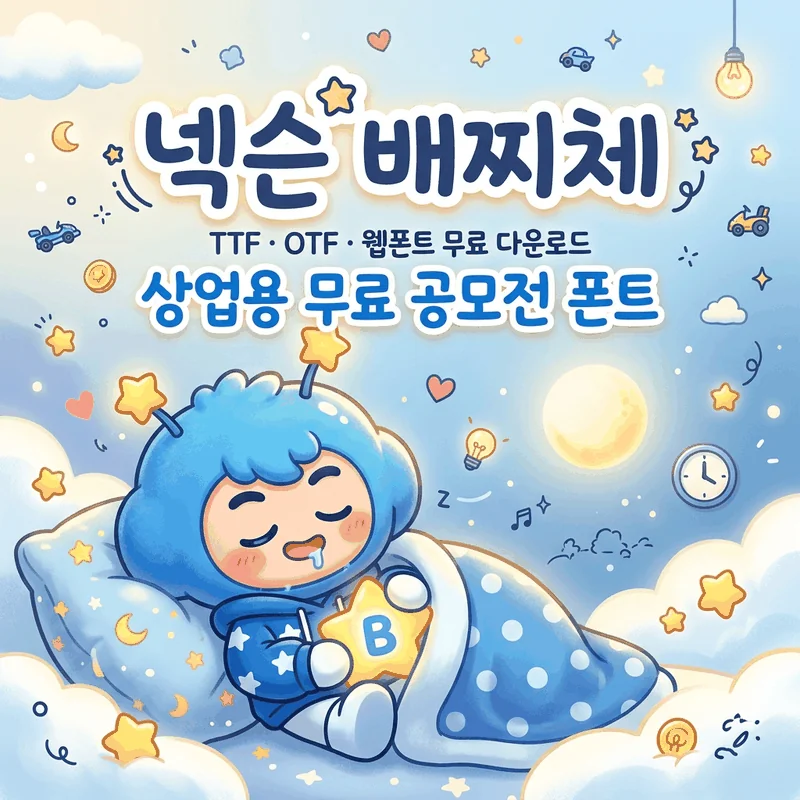
๋ฅ์จ ์บ๋ฆญํฐ ๊ณต๋ชจ์ ์์ ํ์ด๋ '๋ฐฐ์ฐ์ฒด'์ ๋์์ธ ํน์ง, ๊ณต์ ๋ฌด๋ฃ ๊ฒฝ๋ก, ์ ์๊ถ ๋ฒ์, ๊ทธ๋ฆฌ๊ณ ๊ฐค๋ญ์ ์ค๋งํธํฐ ์ ์ฉ๋ฒ๊น์ง ์๋ฒฝ ์ ๋ฆฌํ์ต๋๋ค.
๊ท์ฌ์ด ํฐํธ ํ๋๊ฐ ๋์์ธ ์ ์ฒด๋ฅผ ์ด๋ฆฌ๋ ๊ฒฝํ, ํด๋ณด์ จ๋์? ์ ๋ ์ด๋ฆฐ์ด ๊ต์ก ์ฝํ ์ธ ์ ์บ๋ฆญํฐ ๊ฐ์ฑ์ด ํ์ํ ๋์์ธ ์์ ์ ํ ๋๋ง๋ค ๋ฅ์จ ๋ฐฐ์ฐ์ฒด๋ฅผ ๊บผ๋ด ์ฐ๊ฒ ๋ฉ๋๋ค. ๋ฅ๊ธ๋ฅ๊ธํ๊ณ ํ์ด ๋น ์ง ๋ฏ ์์ฐ์ค๋ฌ์ด ์๊ธ์จ ๋๋์ด ํ๋ฉด์์ ๊ทธ๋๋ก ์ด์๋๋ ์์ฒด์ ๋๋ค.
์ค๋์ ์ด ํฐํธ๋ฅผ ์ง์ ํ์ฉํด์จ ๊ฒฝํ์ ๋ฐํ์ผ๋ก, ๋ฅ์จ ๋ฐฐ์ฐ์ฒด์ ๋ํ ๋ชจ๋ ์ ๋ณด๋ฅผ ์ฌ์ค ๊ทธ๋๋ก ์ ๋ฆฌํด ๋๋ฆฌ๊ฒ ์ต๋๋ค.
1. ๋ฅ์จ ๋ฐฐ์ฐ์ฒด๋? ๊ณต๋ชจ์ ์ถ์ ์์ฒด ๐จ
๋ฅ์จ ๋ฐฐ์ฐ์ฒด๋ (์ฃผ)๋ฅ์จ์ฝ๋ฆฌ์๊ฐ ์ ์ยท๋ฐฐํฌํ ๋ฌด๋ฃ ์๊ธ์จ ํฐํธ์ ๋๋ค. ๋จ์ํ ๋์์ด๋๊ฐ ๋ง๋ ์์ฒด๊ฐ ์๋๋ผ, 2019๋ 5์ ๋ฅ์จ์ด ์งํํ '๋ฐฐ์ฐ ์๊ธ์จ ๊ณต๋ชจ์ '์ ์ต์ฐ์ ์์์ ์ด๋ฏธ์ง๋ฅผ ๊ธฐ๋ฐ์ผ๋ก ์ ์๋์์ต๋๋ค.
๋ฐฐ์ฐ๋ ๋ฅ์จ์ ๋ํ ๊ฒ์ ์บ๋ฆญํฐ๋ก, ๋๊ธํ๊ณ ๋์ฒ์ ์ธ ์ฑ๊ฒฉ์ด ๋งค๋ ฅ์ ๋๋ค. ์ด ํฐํธ ์ญ์ ๋ฐฐ์ฐ์ ์ฑ๊ฒฉ์ฒ๋ผ ์ฒ์ฒํ ๋๊ธํ๊ฒ ์ด ๋ฏํ ๋ฆฌ๋ฌ๊ฐ์ด ํต์ฌ์ ๋๋ค.
2. ๋ฐฐ์ฐ์ฒด์ ๋์์ธ ํต์ฌ ํน์ง 3๊ฐ์ง ๐
โ ๋จ์ผ ๊ตต๊ธฐ์ ์๋๊ฐ ์๋ ์๊ธ์จ
๋ฐฐ์ฐ์ฒด๋ ๋จ์ผ ๊ตต๊ธฐ(Regular) 1์ข ๋ง ์ ๊ณตํ์ง๋ง, ์๊ธ์จ ํน์ ์ ํ๋ง๋ค ๋ค๋ฅธ ๋๊ป ๋ณํ๊ฐ ์์ฐ์ค๋ฝ๊ฒ ๋ด์ฅ๋์ด ๋จ์กฐ๋กญ์ง ์์ต๋๋ค. ๋ฅ๊ธ๋ฅ๊ธํ ๊ณก์ ์์ฃผ๋ก ์น๊ทผํ ๋ถ์๊ธฐ๋ฅผ ์ฐ์ถํฉ๋๋ค.
โก ์ถฉ๋ถํ ๊ธ์ ์ (ํ๊ธ 2,479์)
ํ๊ธ 2,479์, ์๋ฌธ 94์, ์ฌ๋ณผ 986์๋ฅผ ์๋กํ๊ณ ์์ด ์ค๋ฌด ์์ ์์ ๊ธ์๊ฐ ๊นจ์ง๋ ์ผ์ด ๊ฑฐ์ ์์ต๋๋ค. ์๋ฌธ ์ํ๋ฒณ์๋ ๋ฐฐ์ฐ์ฒด ํน์ ์ ์คํ์ผ์ด ์๋ฒฝํ๊ฒ ์ ์ฉ๋์ด ์์ต๋๋ค.
๋ฐฐ์ฐ์ฒด๋ ์ด๋ฆฐ์ด์ฉ ๊ต์ก ์ฝํ ์ธ ๋ ๋ค์ด์ด๋ฆฌ ๊พธ๋ฏธ๊ธฐ, ์บ๋ฆญํฐ ๊ฐ์ฑ์ด ํ์ํ SNS ์นด๋๋ด์ค ๋ฑ์์ ๋ ๋ณด์ ์ธ ์น๊ทผ๊ฐ์ ๋ณด์ฌ์ค๋๋ค. ๋ค๋ง ๊ฒฉ์์ ๊ฐ์ถ ๋น์ฆ๋์ค ๋ฌธ์๋ณด๋ค๋ ๋ถ๋๋ฝ๊ณ ๋ฐ์ ์ปค๋ฎค๋์ผ์ด์ ์ด ํ์ํ ๋์์ธ์ ๊ฐ๋ ฅ ์ถ์ฒํฉ๋๋ค.